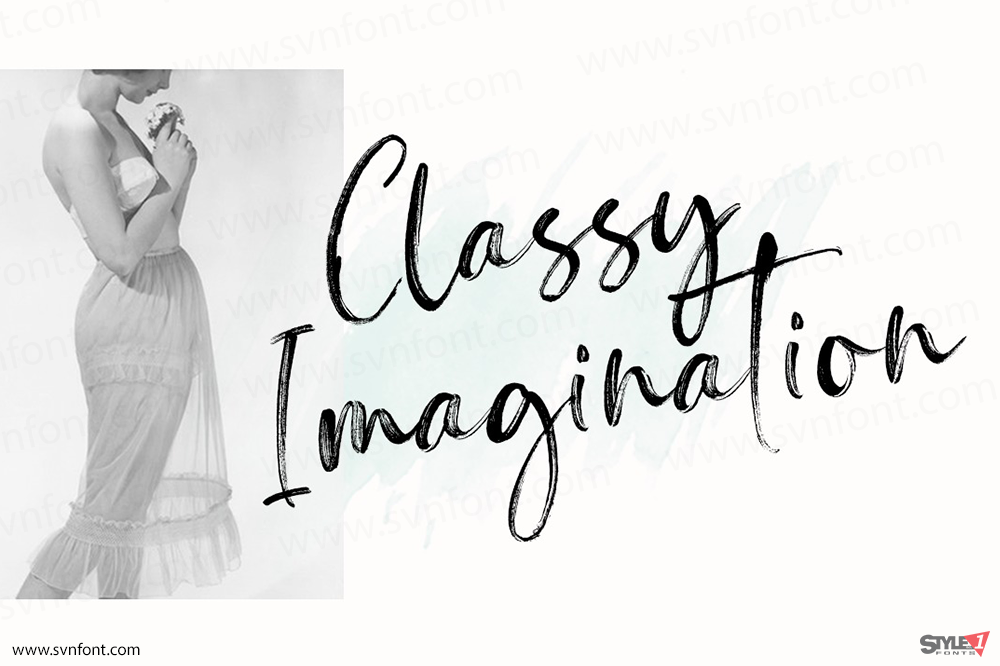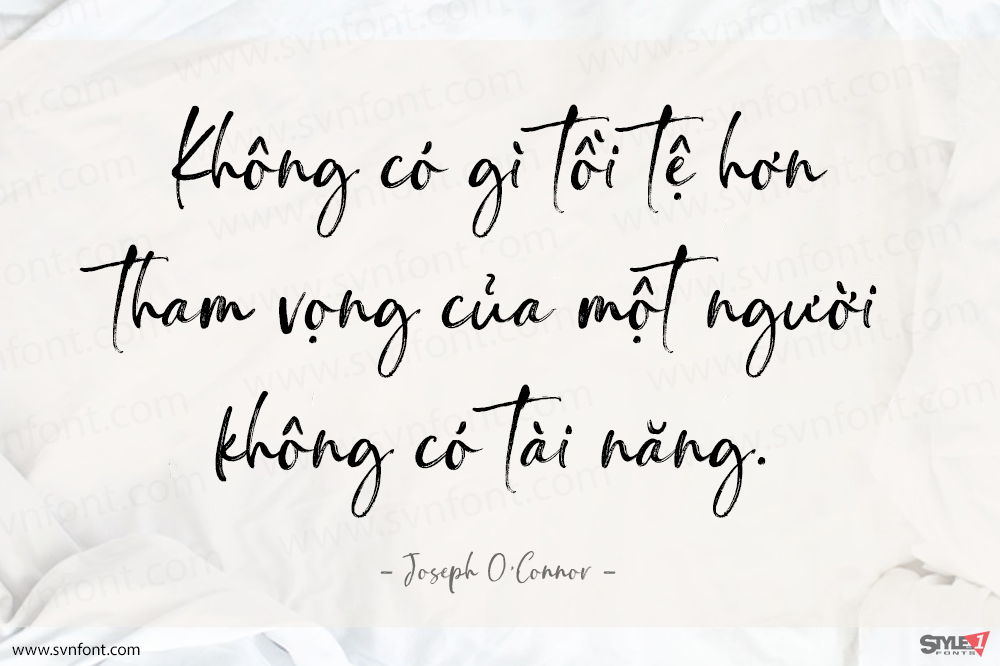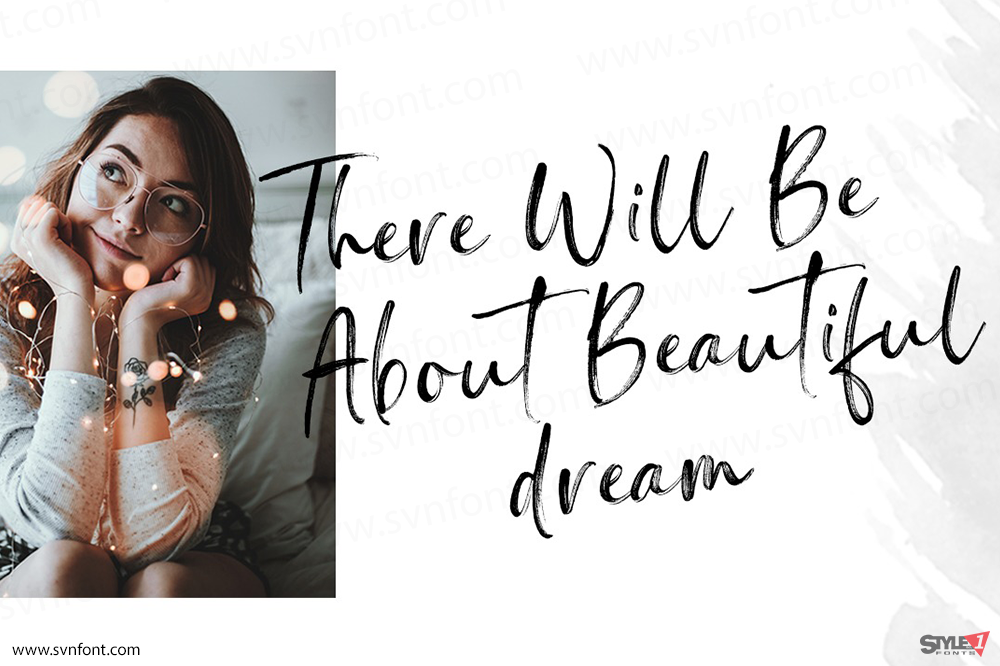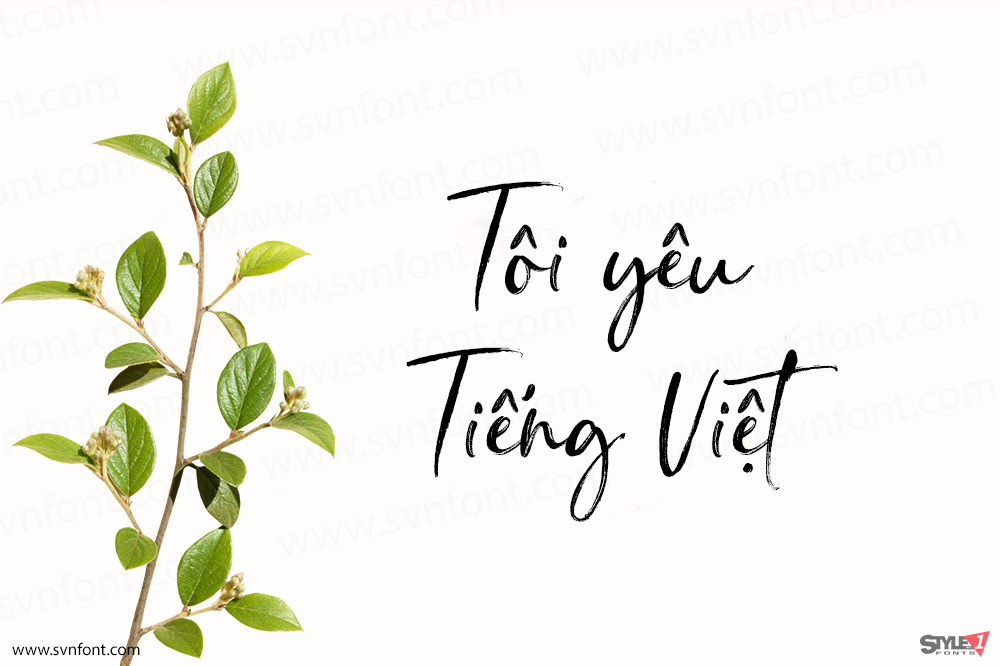
Greatlove là một font script được tạo ra bằng cọ tự nhiên. Được viết bằng những nét nhanh chóng bằng bút cọ khá khô, font này trông đẹp mắt và hoàn hảo cho các thiết kế như tạp chí, logo, bao bì sản phẩm, trích dẫn, áp phích, hàng hóa, thiệp chúc mừng trên mạng xã hội và nhiều hơn nữa.
Nhà thiết kế: Alam Syahril
Nhà phát hành: Realtype